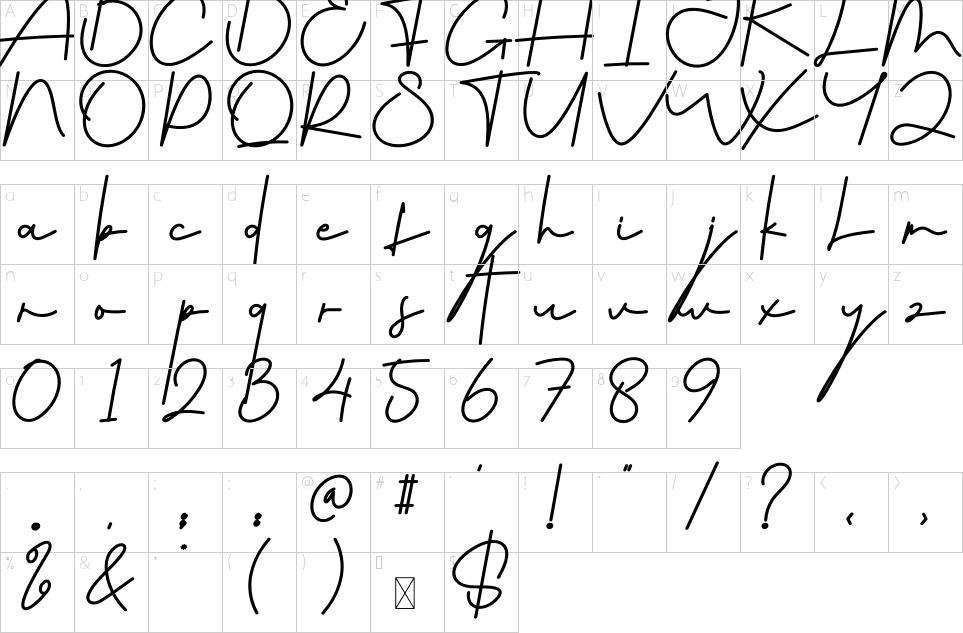
Descubra Montana, uma fonte gratuita que adiciona um toque de simplicidade e elegância a seus projetos digitais. Desenvolvida pelo designer anônimo scratchones, a Montana tem um design minimalista e arredondado, ideal para títulos e headlines. Suavemente personalizada e com uma paleta de cores vasta, essa fonte é perfeita para criar designs gráficos modernos e minimalistas. Montana não só é uma excelente escolha para projetos de design editorial, como também se destaca em sites, blogs e designs de aplicativos. Com seu estilo limpo e elegante, é uma fonte ideal para designers em busca de uma solução versátil e fácil de usar. Montana está disponível tanto para Windows quanto para Mac, facilitando o seu uso em diferentes plataformas. Descubra por si mesmo como Montana pode transformar seus projetos digitais em algo único e elegante.